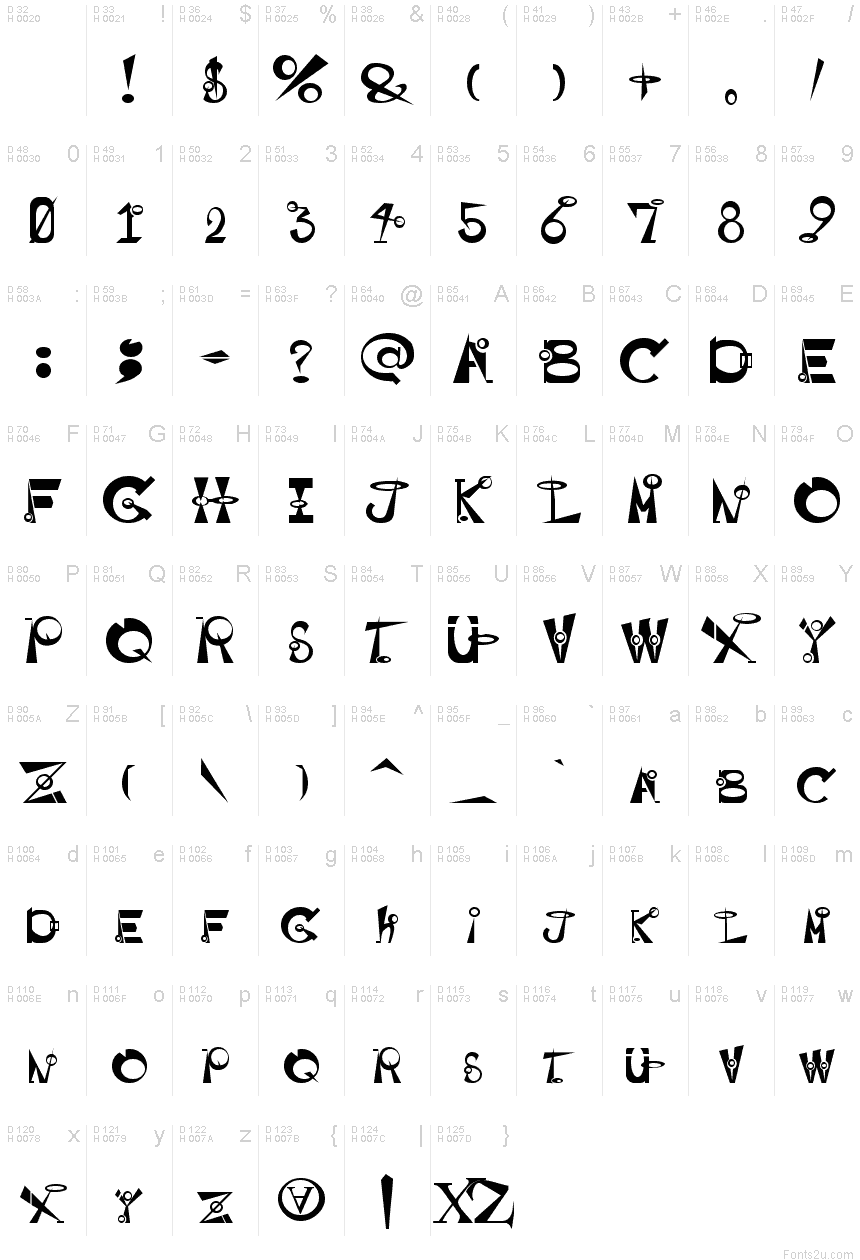
<p>Font BASEHEAD autorstwa Terrence’a Calcium z Xone Zero Productions to darmowy, dekoracyjny krój wyświetlaniowy, który wygląda jak wyjęty prosto z ulotki na nocną imprezę rave. Wysokie, przypominające kolce formy zderzają się z okrągłymi, bąbelkowymi wypełnieniami liter, tworząc nerwowy, elektryzujący rytm, który jest jednocześnie w stylu retro-techno i nieco szalony. Litery zazębiają się i nakładają na siebie, dzięki czemu słowa stają się zwartymi, graficznymi znakami, a nie tylko zwykłym tekstem.</p><p>Używając BASEHEAD, Twoje nagłówki od razu nabierają hałaśliwego, elektrycznego charakteru, co doskonale sprawdza się w przypadku plakatów klubowych, eksperymentalnych okładek albumów, fanzinów, banerów internetowych i logotypów z efektem glitch. Ten darmowy font świetnie wygląda w dużych rozmiarach, gdzie jego atramentowe nakładki i koliste detale pozostają wyraźne. Połącz go z prostym, wąskim krojem bezszeryfowym w tekście głównym, aby utrzymać chaos w ryzach.</p>